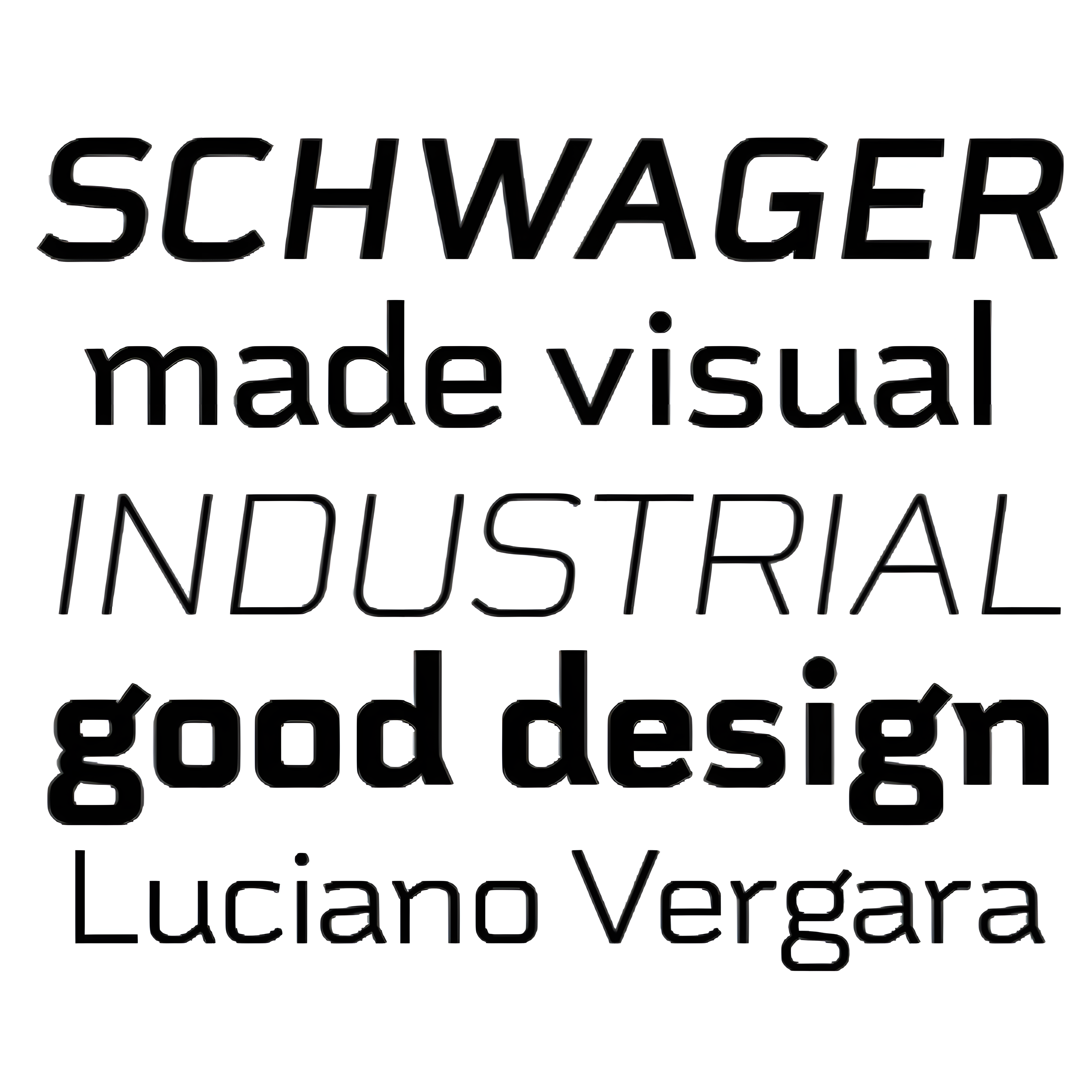
Schwager Sans
| Año | 2014 |
| Créditos | Luciano Vergara |
| Descripción | El diseño de Schwager Sans se basa en la fuente Schwager. Muy adecuada para títulos, portadas de libros y revistas, logotipos y sitios web. |
| Clasificación | Texto |
| Estilos | 12 |